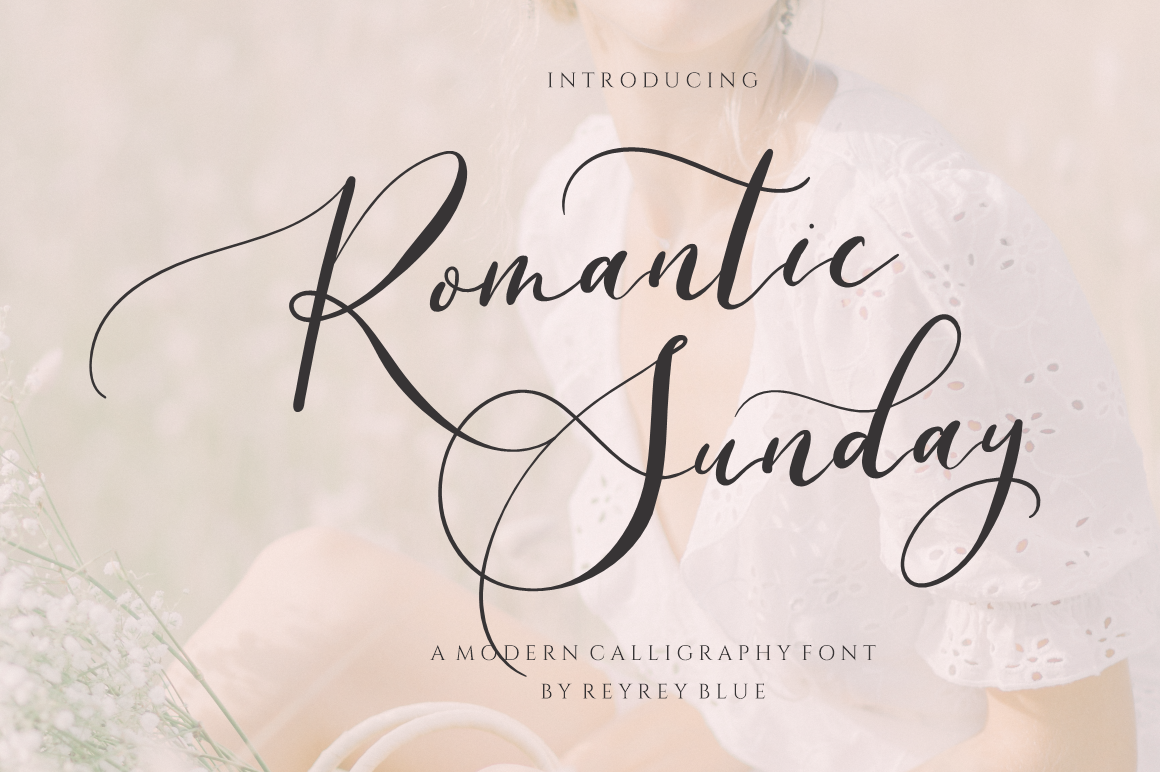
Romantic Sunday Font – Download Grátis
Romantic Sunday Font é uma nova e maravilhosa fonte que traz uma sensação contemporânea e elegante ao seu design. Com sua tipografia fluida e arredondada, ela cai perfeitamente para projetos pessoais ou até mesmo para elementos de newsletter com um toque romântico e sofisticado. Ideal tanto para textos de texto quanto para títulos, esta fonte traz uma qualidade única que adicionará um charme especial a qualquer projeto onde for utilizada. Foi criada pelo talentoso designer ReyreyBlue, garantindo que cada caractere seja perfeitamente bem-sucedido em sua função. Seja para criar um design gráfico sofisticado ou simplesmente personalizar mensagens pessoais com elegância, Romantic Sunday Font é uma escolha ideal para designers apaixonados por textos e gráficos.